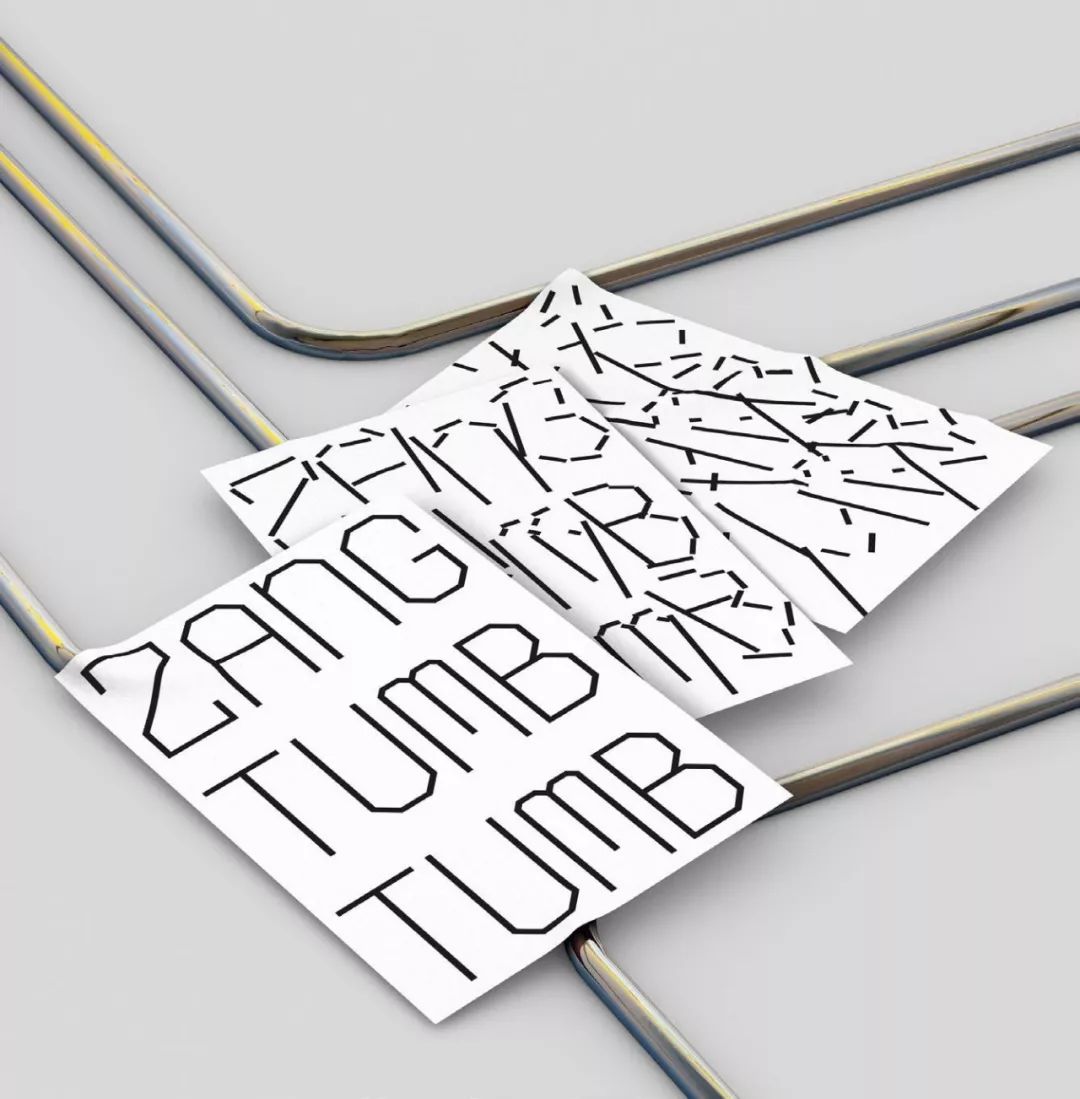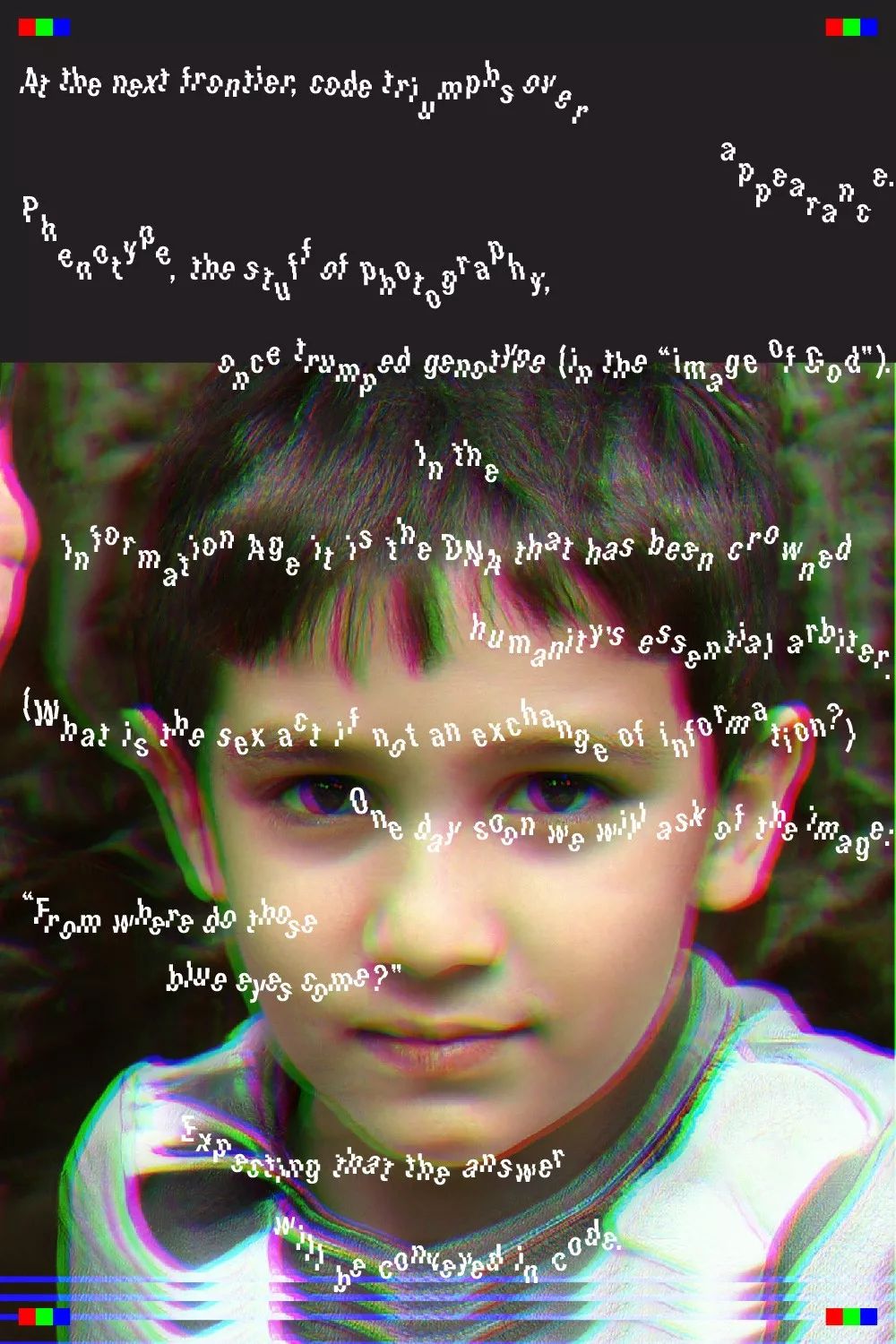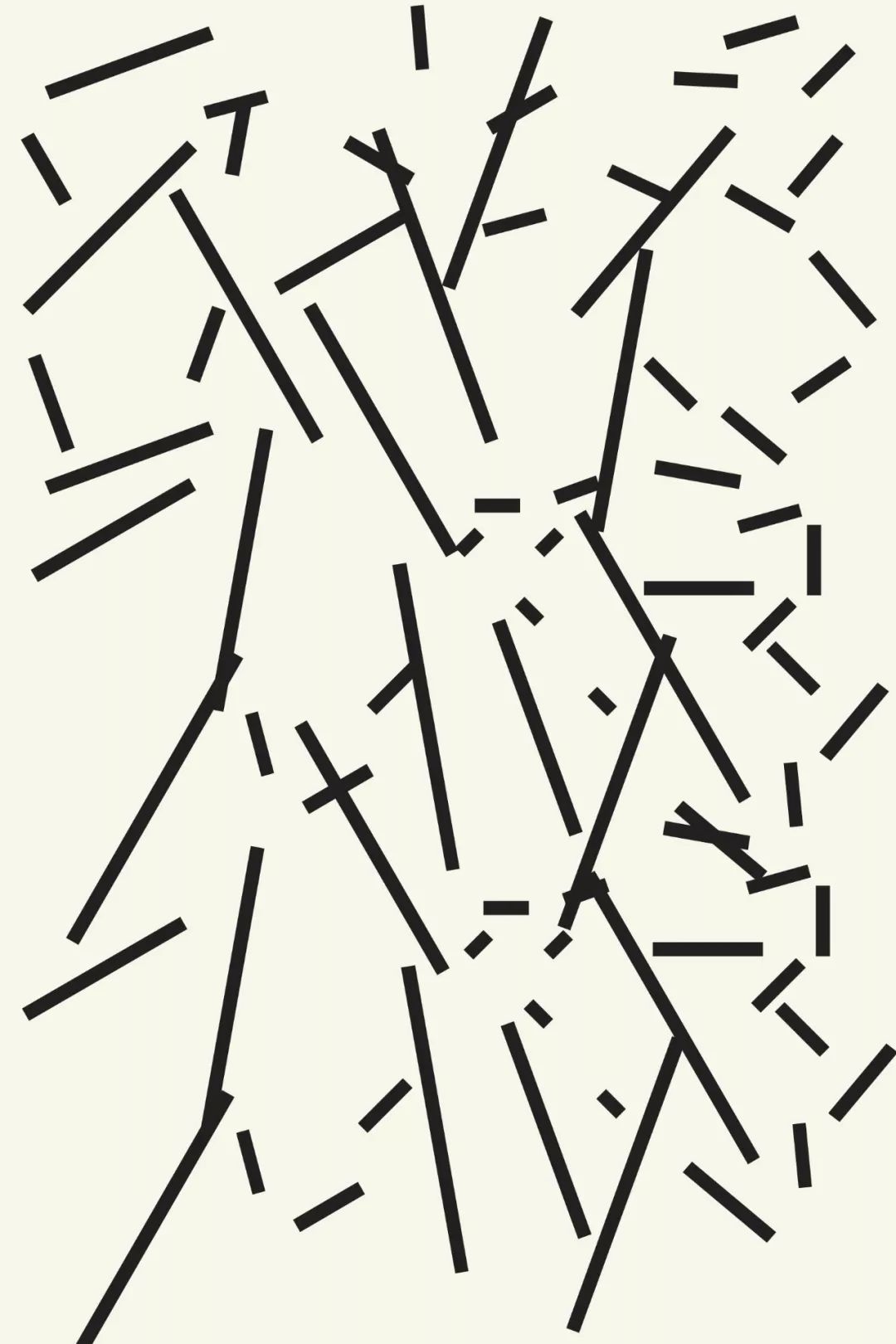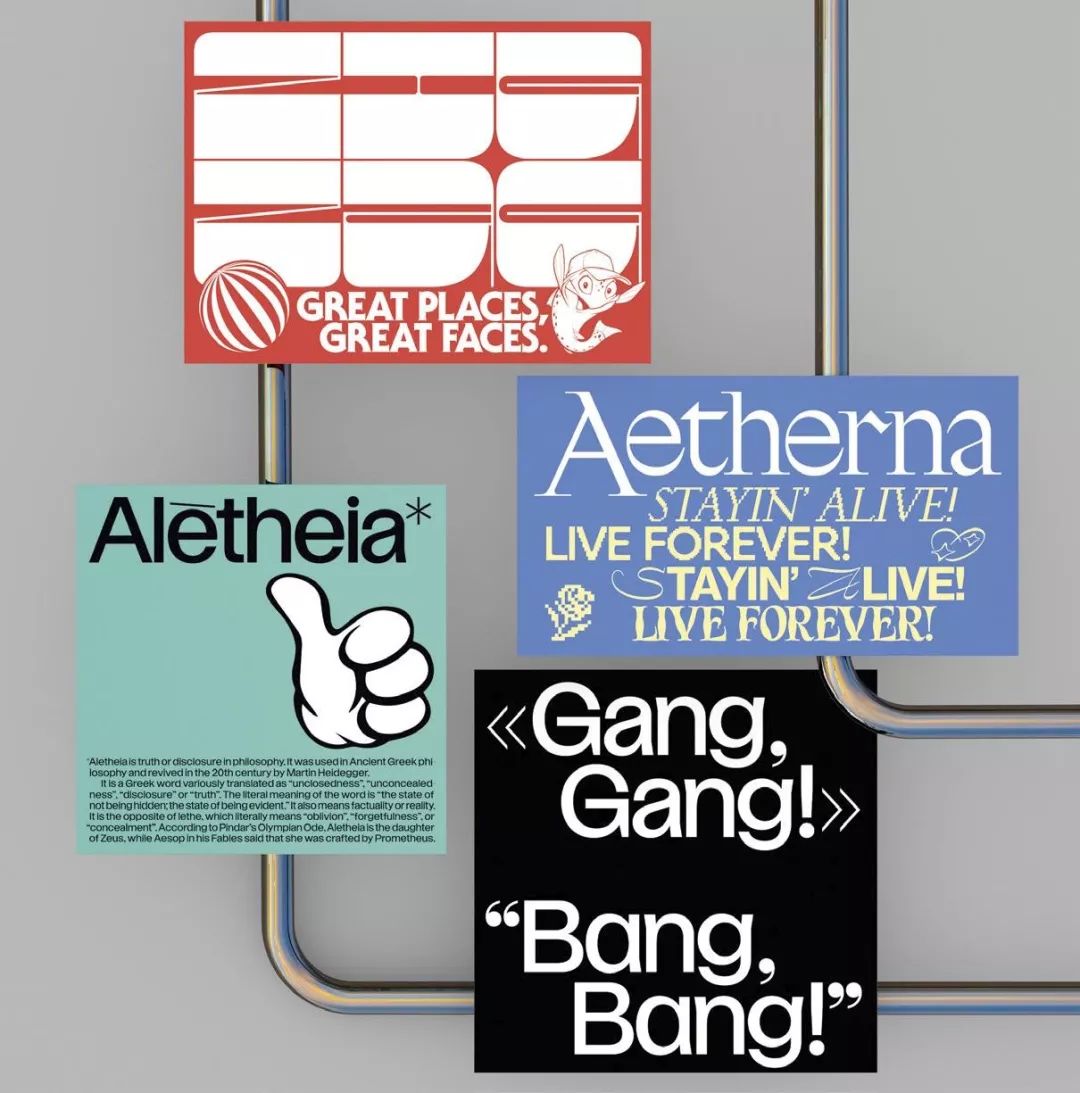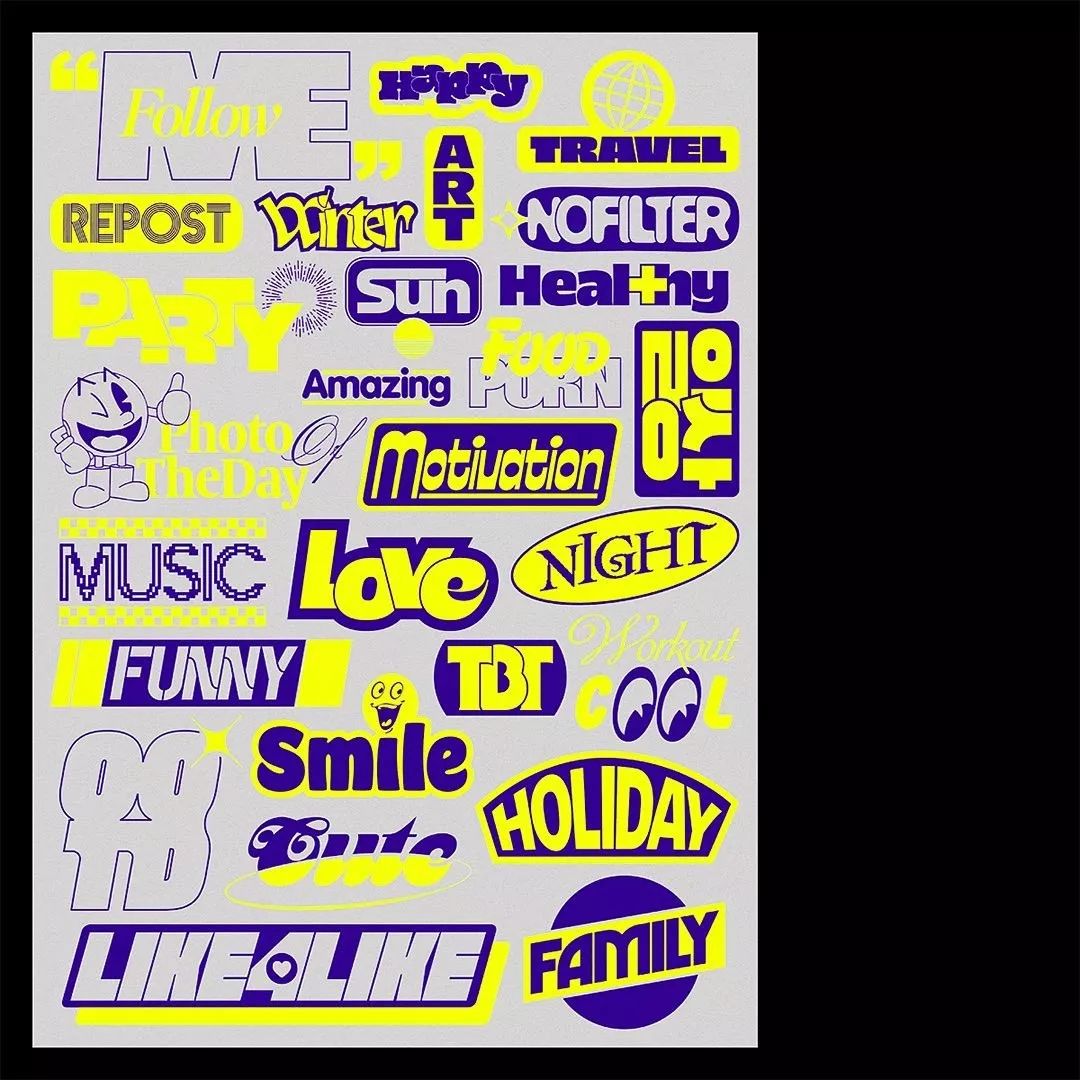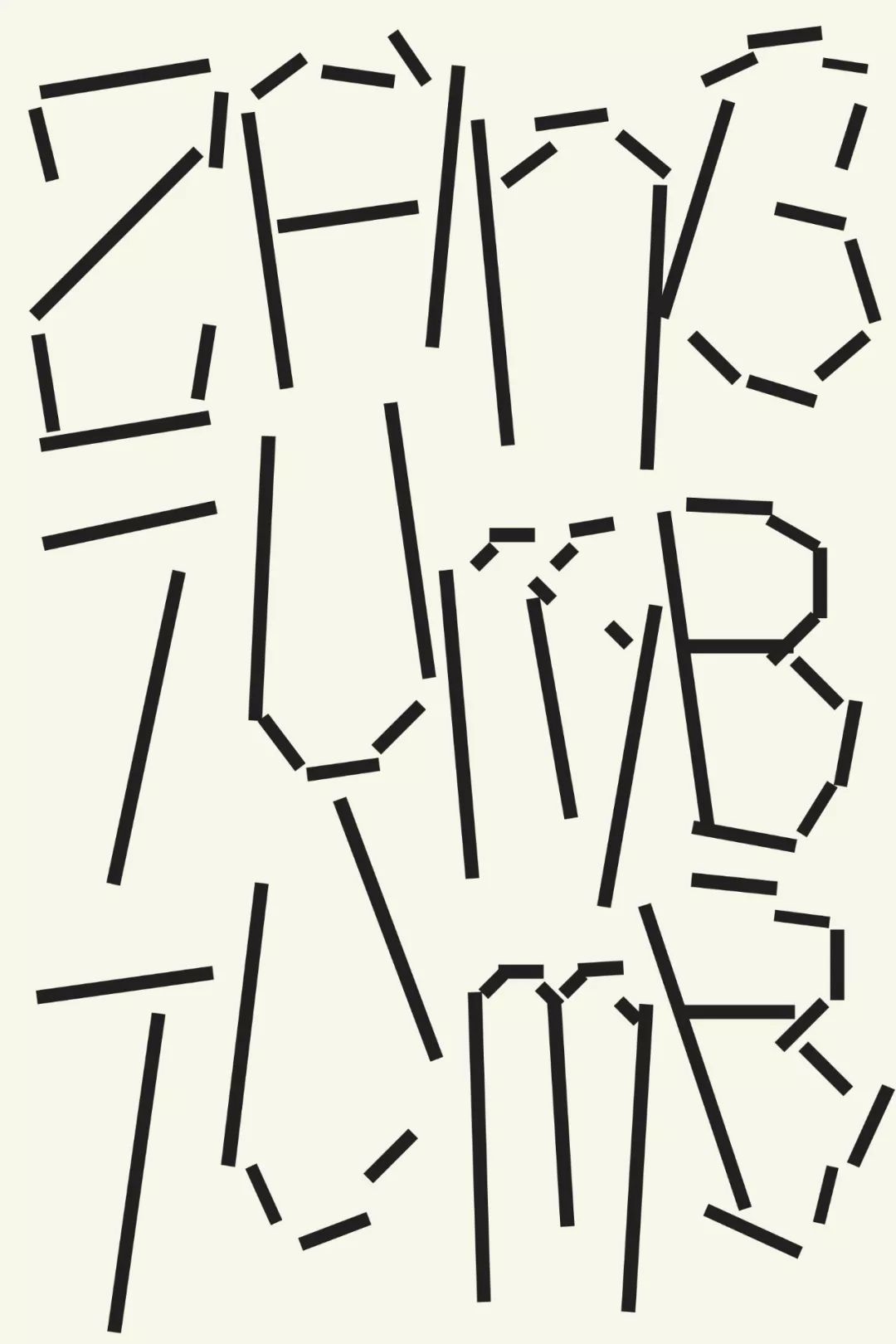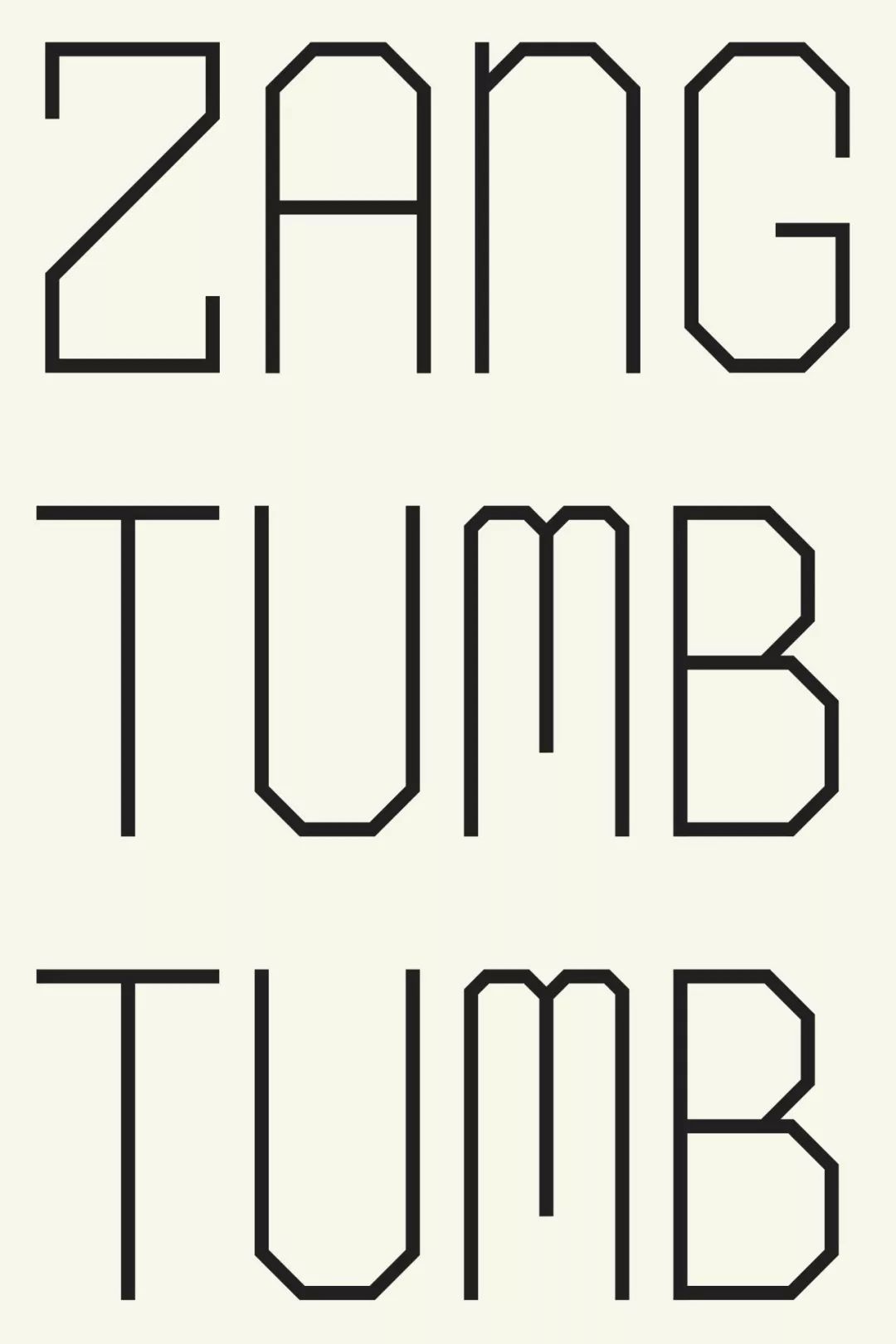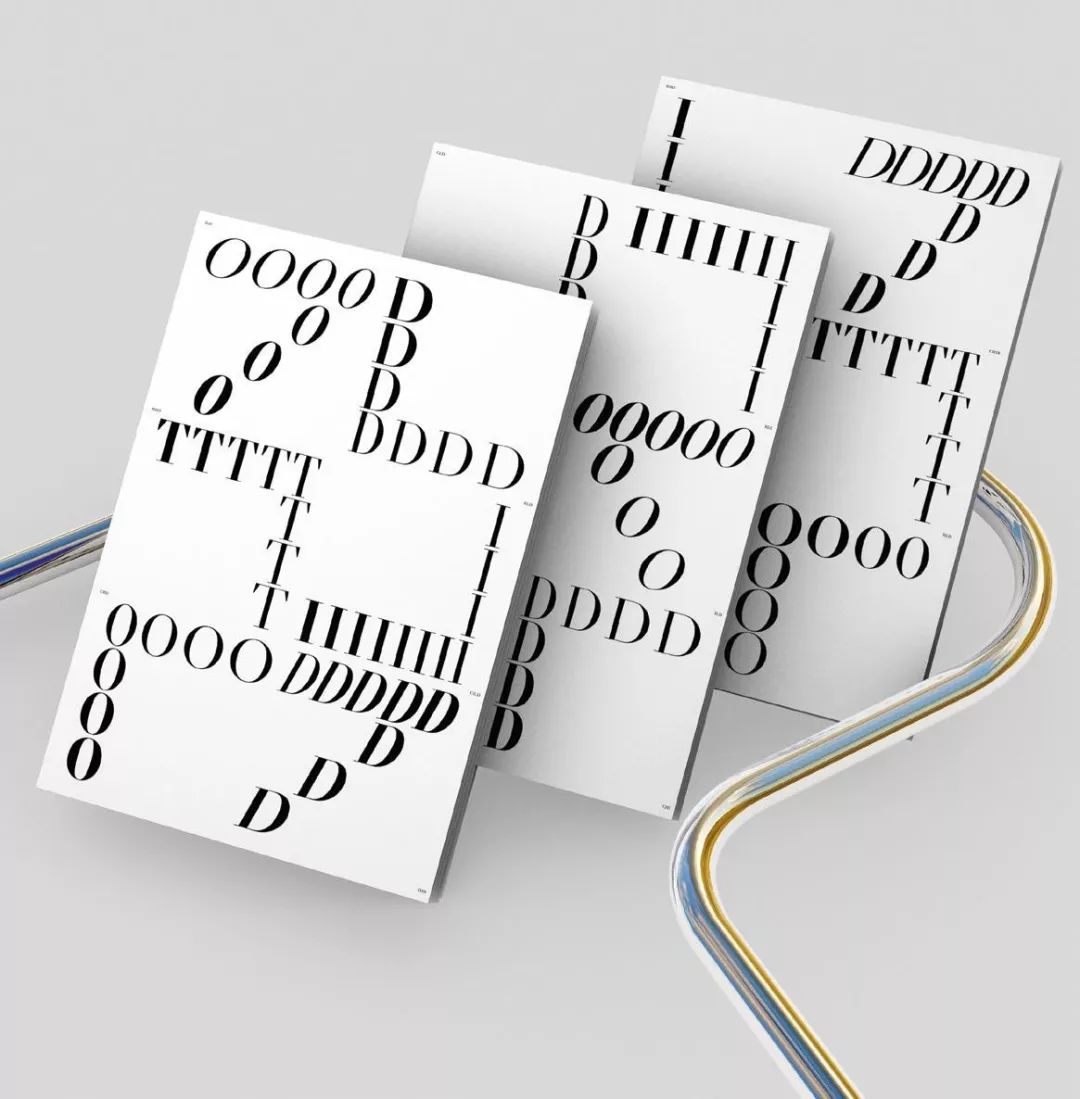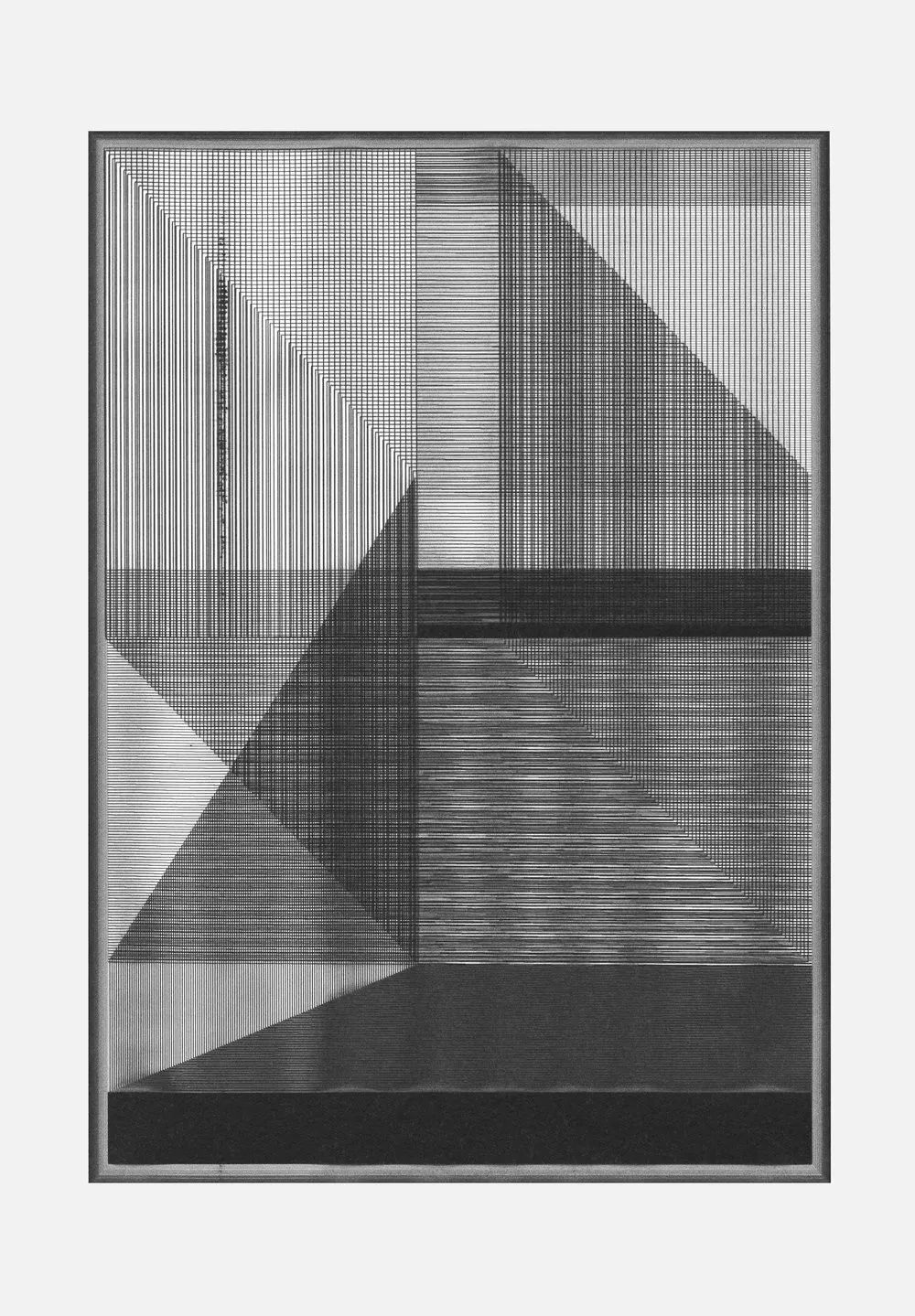
视觉传达领域的年轻新血液
视觉传达的产业已经变得比以往任何时候都更大且更加复杂,因此我们(Wallpaper)每年对毕业生们的挑选也变得越来越难。以下这些我们挑选出来的今年最佳传达设计,版式设计,图形设计等。
Barrett 设计的可变字体实验性地探索了文本与图像的关系,试图将“平面设计”作为图像化的文本注入当代数字环境中去”。梦想合作者:Dan Deacon, Nam June Paik. “我同样热爱城市交通系统的标识设计。”🔗 http://micahbarrett.work/Hugo Dumont and Anthony Vernerey这对法国搭档的联合设计项目构建了一个未来的 Instagram 世界,用平面设计来想象另类未来。“我们对社交网络会创造一个形式盖过内容的虚假的世界的说法持怀疑态度。”🔗 hugodumont.co; @anthony_vernerey这个项目的设计师 Peter 曾言“我对宗教仪式面具抱有的浓烈兴趣是这个项目的出发点”。他的作品《Mask》,包含了平面设计和织物设计,其中有一条用于蒙面的丝巾,或隐藏,或揭示地用“图形过渡”的方式向世界展示神秘的蒙面艺术。🔗 http://aureliapeter.ch/Haslauer 活力四射的海报设计仅仅通过版式上的设计就做到了将流行音乐和爵士乐的美学和感性融合在一起。“Niklaus Troxler 是我的灵感来源,他曾在 ABK 任教,是最棒的爵士乐美学大师。梦想合作者:艺术家兼气味研究员 Sissel Tolaas
🔗 http://haseaufderlauer.com/Ziv的“动态网格”使用随机的网格来改变排版和布局。“我开始思考如何利用现有的系统来变形和陌生化现有的字体。”Ziv 设计了26本字母表小册子,每一个字母都被机器生成的代码所改变。Molnár 的版式设计作品探索了一个名为 Didot 的早期 serif 字体家族,该字体以法国打印机和字体先驱 Firmin Didot 命名。Molnár 将 Didot 的重新运用在现代媒介中赋予了其新的时代价值。梦想合作者:荷兰设计师 Erik van Blokland该作品聚焦于日本哲学家 Kitarō Nishida 的虚无美学,这一美学思想包含了 Kengo Kuma 和 Richard Neutra 文章在内的相近理念。Tania Alvarez Zaldivar使用了独具个人风格的线条构成的密集图示来说明了这一美学观念和文章。梦想合作者:Isamu Noguchi, Patricia Urquiola🔗 http://zaldivartania.com/《先生夫人》是由 Skop 公司编写、配图和排版的限量版中篇小说,这本书描写了“男人和女人在社会中不断变化的角色”。这名来自捷克的设计师在这本小说的版式设计中,大胆的将插图放在了小说文字的中间位置,他说“我想创作一部图画小说”。梦想合作者:Nicholas NegroponteCsocsan 将 Zorn 描述为“一种计划外的字体”。这一字体是经由捕捉字体动感的瞬间和草稿随意的感觉对比而意外设计出来的。她说:“这种对比不是一成不变的,所以这些字母给人一种奇妙的感觉。”梦想合作者:Hassan Rahim,Kasper-Florio🔗 http://lauracsocsan.com